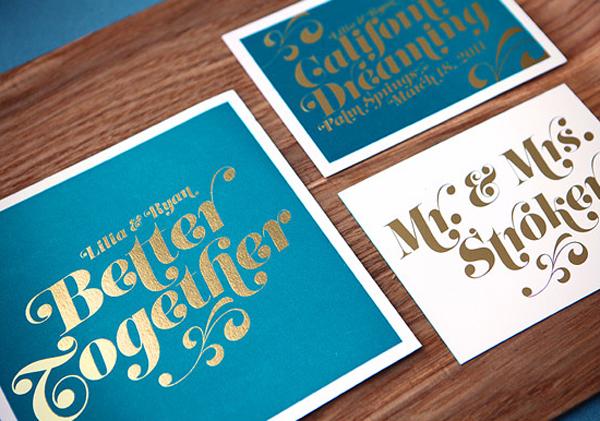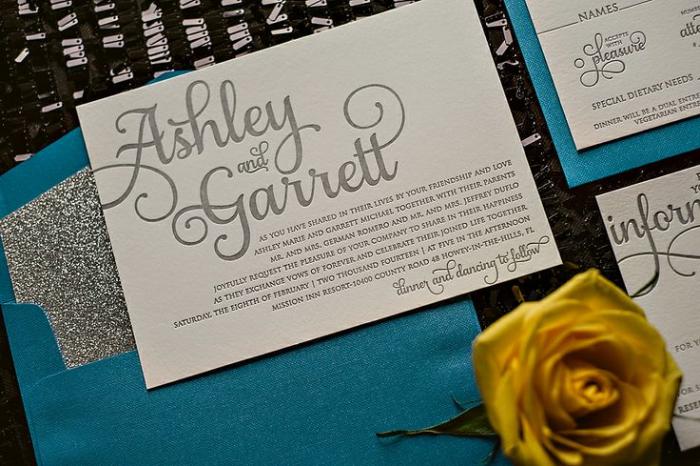
[Mitglied Vawe…] Geschrieben März 26, 2014 Teilen Geschrieben März 26, 2014 Ich bin auf der Suche nach dieser Schrift... Vielen Dank für Eure Hilfe Link zu diesem Kommentar
Beste Antwort [Mitglied Thie…] Geschrieben März 26, 2014 Beste Antwort Teilen Geschrieben März 26, 2014 für mich sieht das aus wie die eloquent von jason walcott, zu lizenzieren bei veer. das meiste ist aus der kursiven gesetzt und mit so vielen schwungbuchstaben wie möglich. 1 Link zu diesem Kommentar
[Mitglied Vawe…] Geschrieben März 26, 2014 Themen-Ersteller Teilen Geschrieben März 26, 2014 Sorry, dass ich nochmal störe, aber das T von Together ist auch wieder eine ganz andere Schrift,oder? Link zu diesem Kommentar
[Mitglied Robe…] Geschrieben März 26, 2014 Teilen Geschrieben März 26, 2014 Sieht nach der einer Swashform oder einem alternativen Zeichen in italic aus, gibts aber bei Veer so nicht. 1 Link zu diesem Kommentar
[Mitglied Thie…] Geschrieben März 26, 2014 Teilen Geschrieben März 26, 2014 doch, gibt es bei veer – und zwar hier (vierte zeile von unten, halblinks). 1 Link zu diesem Kommentar
[Mitglied Vawe…] Geschrieben Mai 14, 2014 Themen-Ersteller Teilen Geschrieben Mai 14, 2014 Ich bin wieder auf der Suche nach einer Schrift...Da sie der vorherigen Schrift ähnelt poste ich es gleich hier rein :) Ich hoffe jemand kann mir helfen. Danke schonmal im Vorraus! Link zu diesem Kommentar
[Mitglied 43ef…] Geschrieben Mai 14, 2014 Teilen Geschrieben Mai 14, 2014 https://www.myfonts.com/fonts/laura-worthington/samantha-upright-script/upright-swash-bold/?meta=/220734/Ashley/Samantha+Upright+SWASH+Bold https://www.myfonts.com/fonts/laura-worthington/samantha-upright-script/ Link zu diesem Kommentar